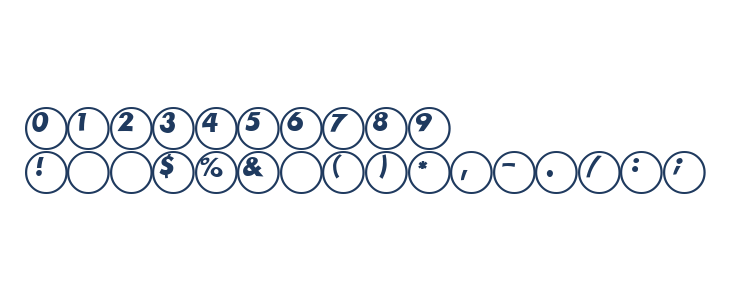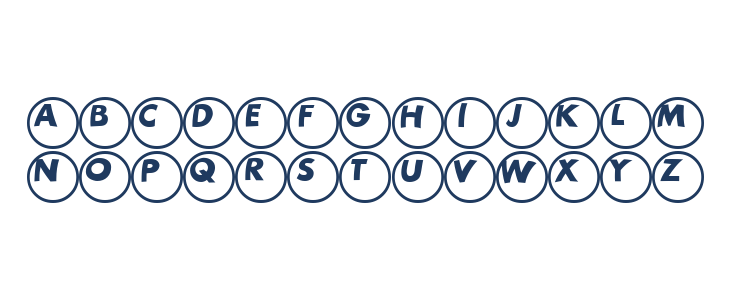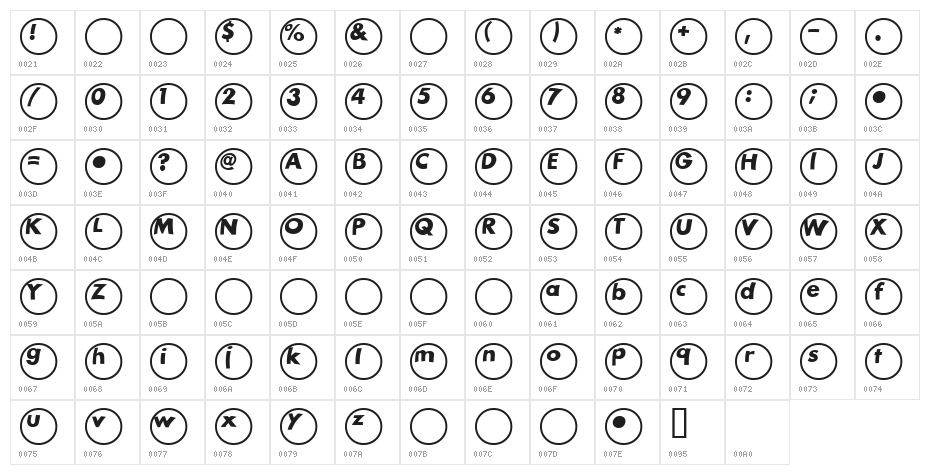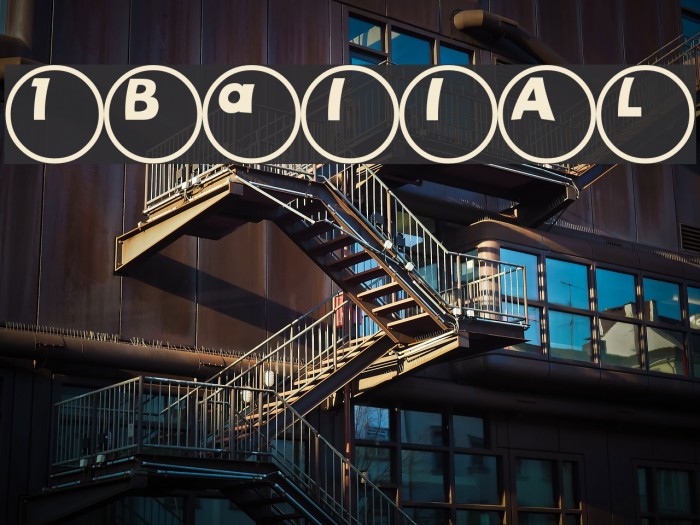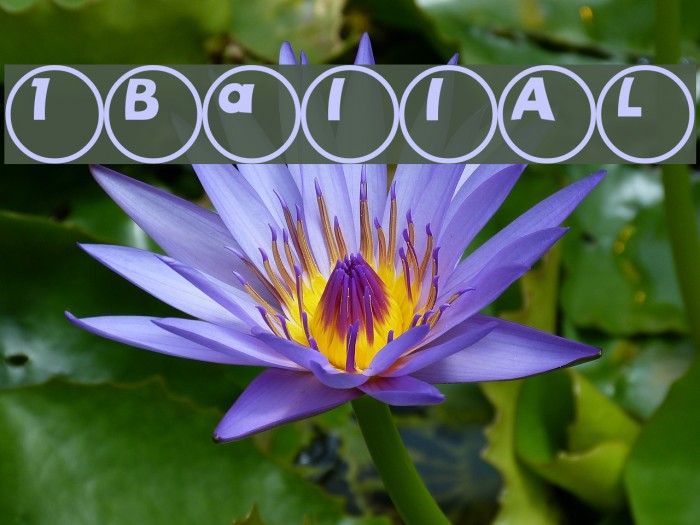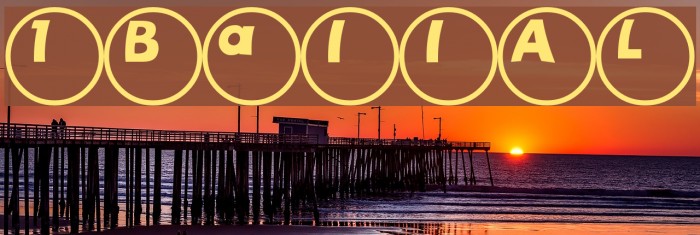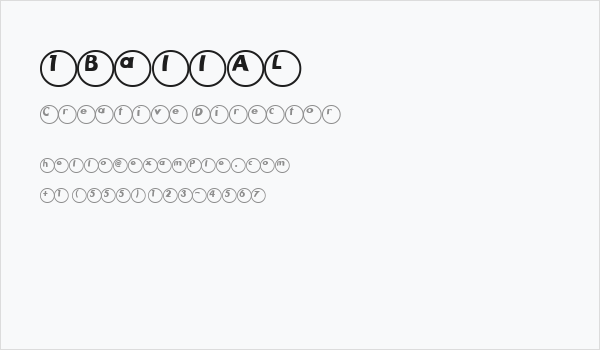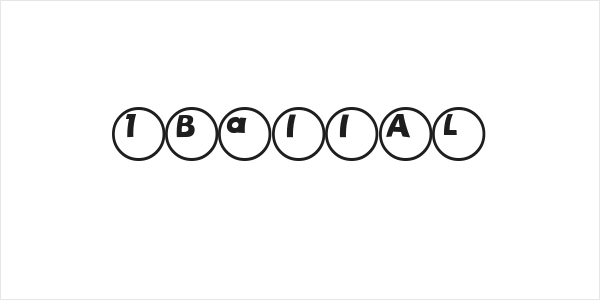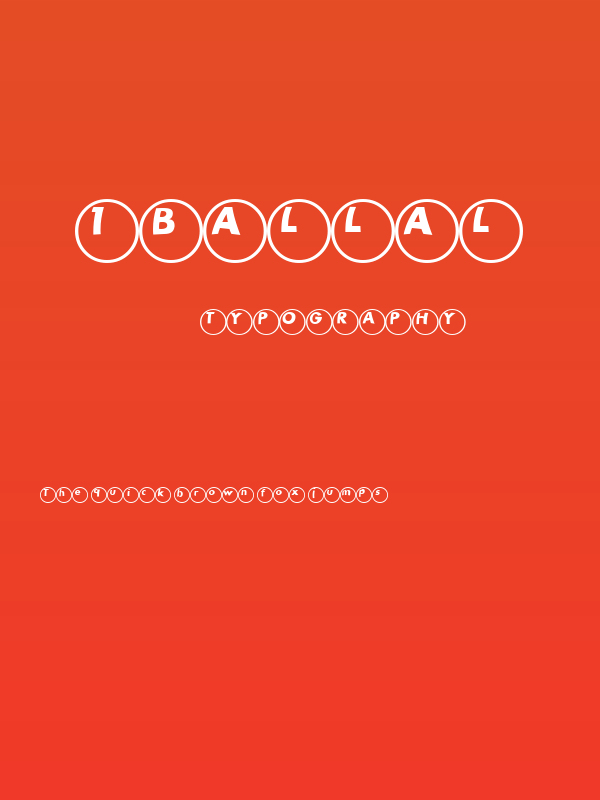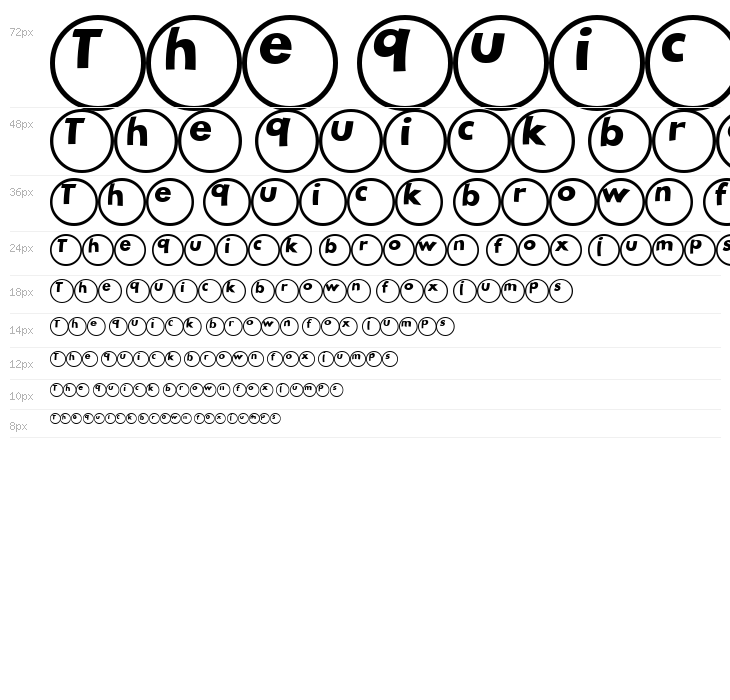
1BallAL Font
| Stile generale | Playful, Decorative |
| Progetti proposti | Ideal for children's books, playful branding, creative posters, and educational materials. |